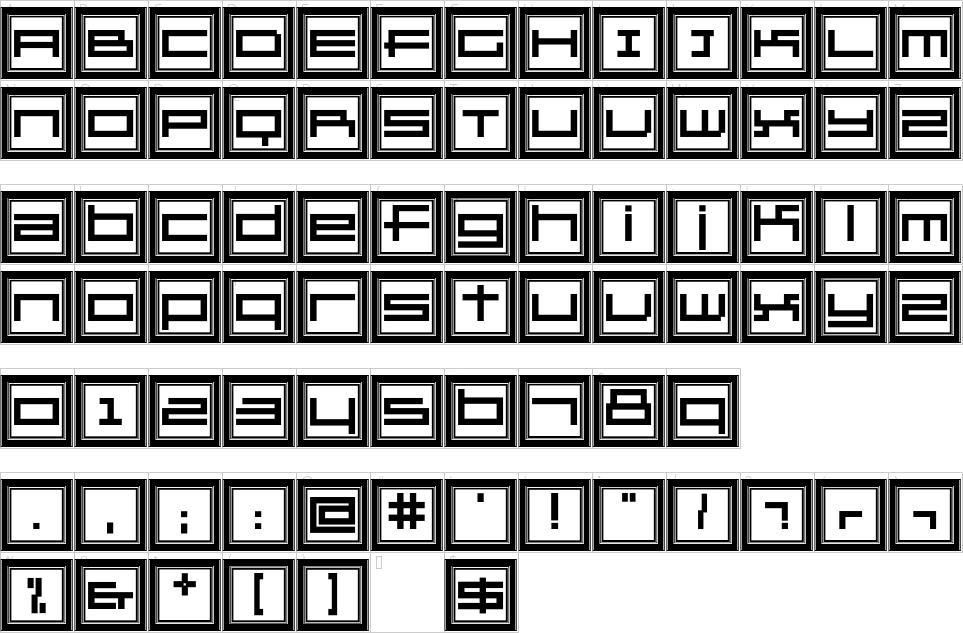
GridEx Gallery é uma fonte gráfica que oferece um formato agradável e versátil para projetos digitais. Desenvolvida por Manfred Klein, essa fonte vem em versões para Windows e Mac, permitindo que os designers adquiram um recurso visual poderoso sem custos. Com sua estrutura de linhas definida e uma tipografia elegante, GridEx Gallery é uma ótima escolha para criações que exigem estilo e elegância. Com downloads que atingiram mais de 5.182 vezes, é fácil ver que essa fonte é um recurso popular e valorizado entre designers de gráficos. Em um mundo de opções de fontes, GridEx Gallery é uma escolha que se destaca por sua qualidade e simplicidade, oferecendo um tom agradável e uma consistência visual sólida para seus projetos.